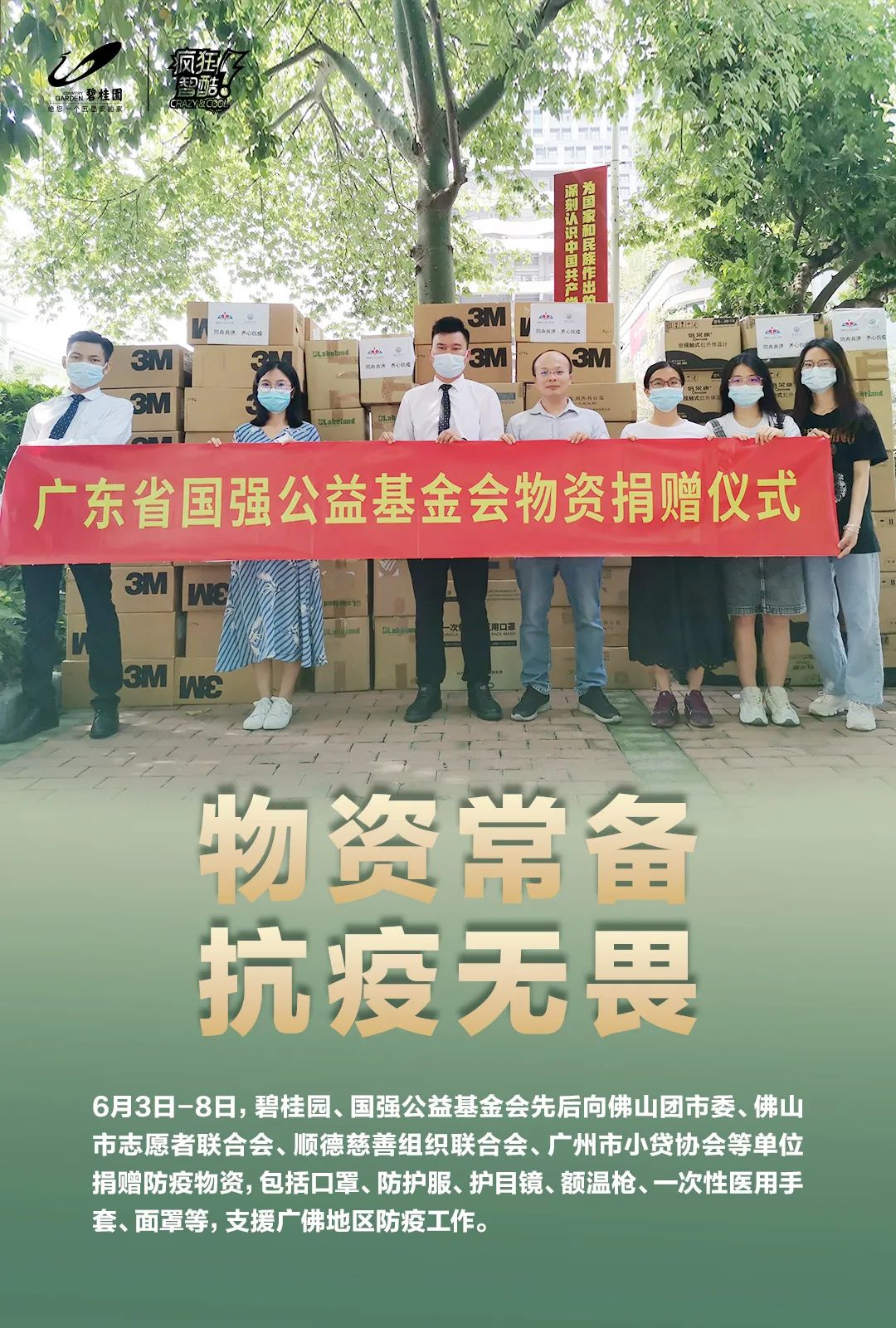
方正Yoonche前卫黑家族
YoondesignGroupInc.
《方正Yoonche前卫黑家族》是方正字库和韩国Yoon Design联合推出的一款中文化多字重字体。基于Yoon Design创造的最真实的韩国字体‘Yoonche’,体现了韩国独特的美学和《训民正音》的精神。
该字体整体设计呈现出强烈的现代设计风格,在笔画和结构的处理上,打破了人们对于黑体的常规认知,结体简洁流畅,没有过多的装饰和复杂的细节。笔形设计硬朗,干净利落,传达出坚定、自信的情绪。
这款字体家族有四种字重样式可供选择,为设计师提供了更广泛的创作空间和可能。该字体整体上给人一种时尚、潮流的视觉感受,适合用于体现科技感、创新感的设计中,对于需要突出品牌个性或特定场景也非常适用。在短视频中,亦具有较高的辨识度和良好的表现效果。